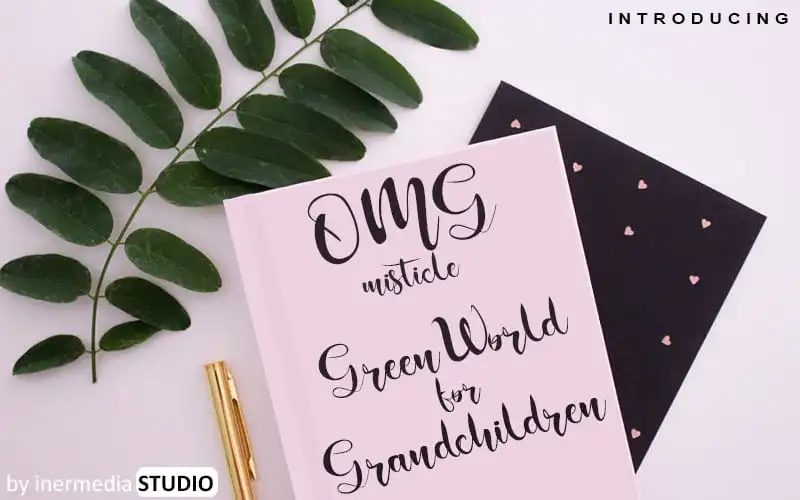
OMG Misticle Script Font
A “OMG Misticle Script Font” é uma opção ideal para quem busca um estilo elegante e moderno ao mesmo tempo. Ela mantém a influência do xamanismo na tipografia enquanto apresenta elementos contemporâneos, fazendo-a perfeitamente adaptável para diversos propósitos de projeto gráfico. Suas linhas fluidas e sua estrutura sofisticada permitem um uso que vai desde criações de cartão postal até selos empresariais e até mesmo a designação de títulos em estilos digitais. Este font é uma escolha versátil para profissionais criativos, oferecendo flexibilidade e capacidade de transformar projetos iniciais com simples alterações na forma do texto. O “OMG Misticle Script Font” combina elegância tradicional com um toque inovador, resultando num recurso gráfico que vai agradar designers de todo o mundo.